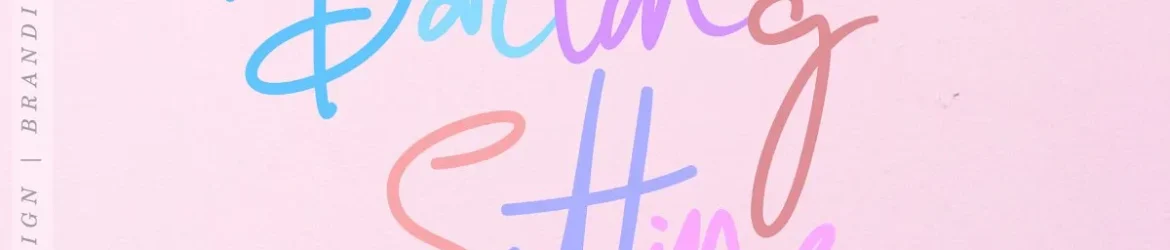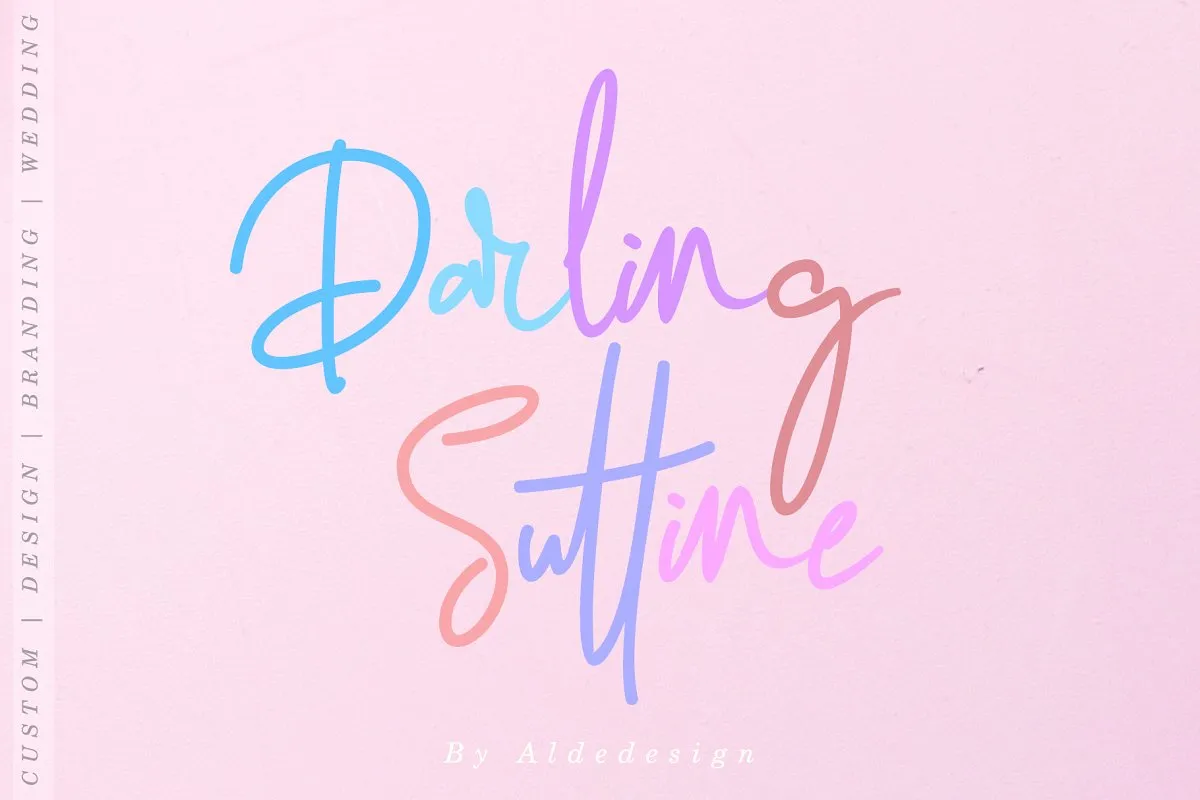
Darling Suttine Signature Font – Fonte Grátis
Darling Suttine Signature Font
Aqui está uma descrição para a página de download da fonte ‘Darling Suttine Signature Font’, adaptada ao tom solicitado: A fonte “Darling Suttine Signature”, criada pelo designer C00zona, é um tipo de letra assinatura com personalidade e estilo. Introduzimos nesta categoria de fontes de escrita, a Darling Suttine Signature traz uma sensação única à sua tipografia. Desenhada por Aldedesign, esta fonte assume um carácter moderno e fresco. Ela contém muitos ligadores naturais e um toque especial que a tornam fácil de ler e imbuí-la de elegância. É perfeitamente adequada para criar design gráfico sofisticado, estilo ou totalmente casual. Darling Suttine Signature é uma escolha ótima tanto para aqueles profissionais que desejam expressar seu trabalho com um toque mais personalizado, quanto para designers buscando adicionar elementos de escrita antiga aos seus projetos. Com sua qualidade e facilidade de uso, esta fonte será a perfeita companheira em qualquer projeto. Esta é uma fonte ideal para criar gráficos profissionais que exigem um toque amigável e moderno. Seja você um designer ou criador de materiais digitais, “Darling Suttine Signature” pode fazer a diferença em sua marca com seu estilo elegante e irresistivelmente acessível.